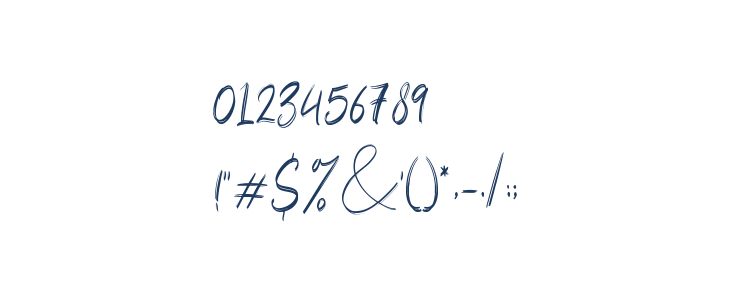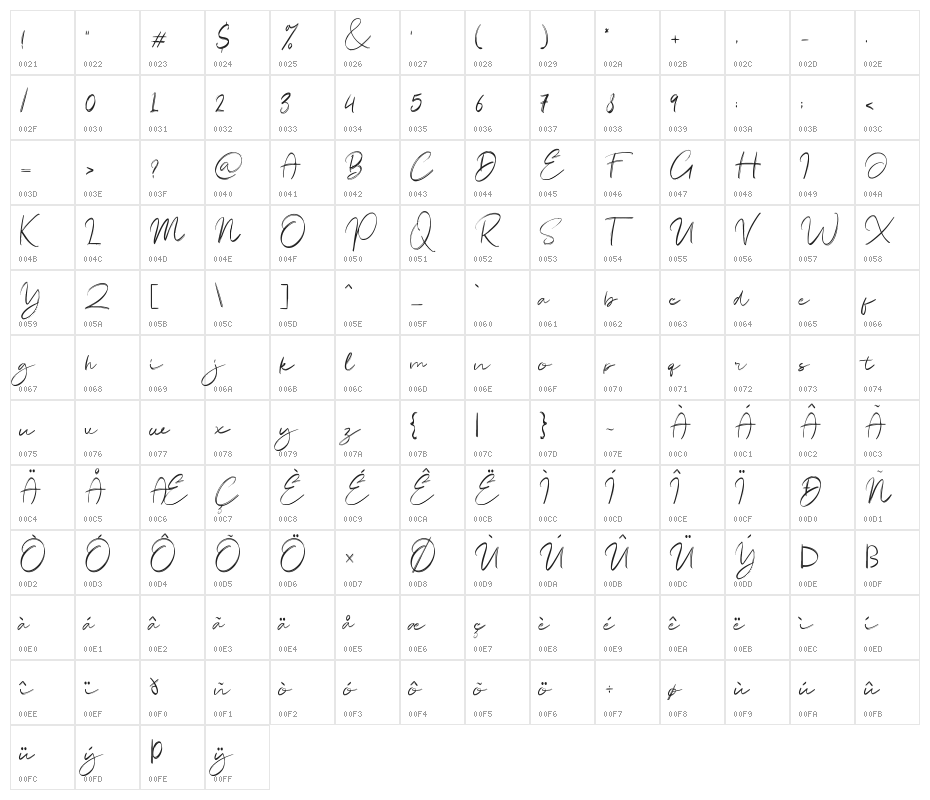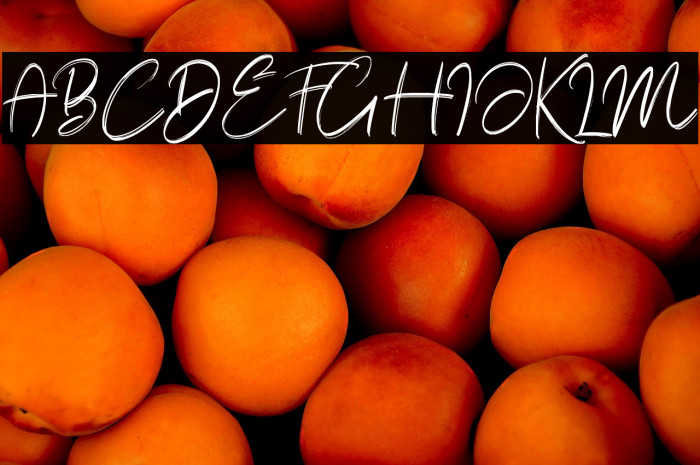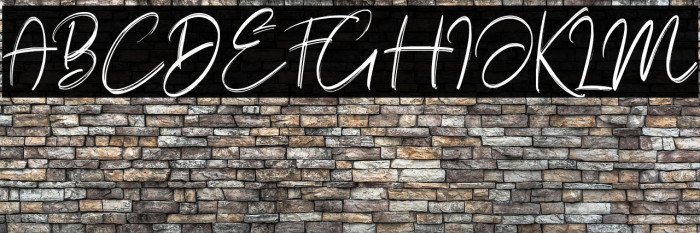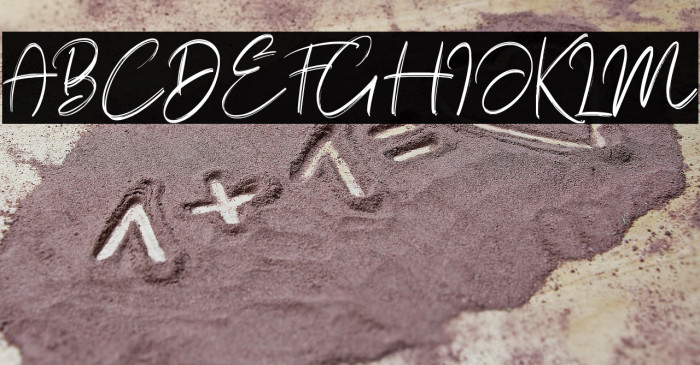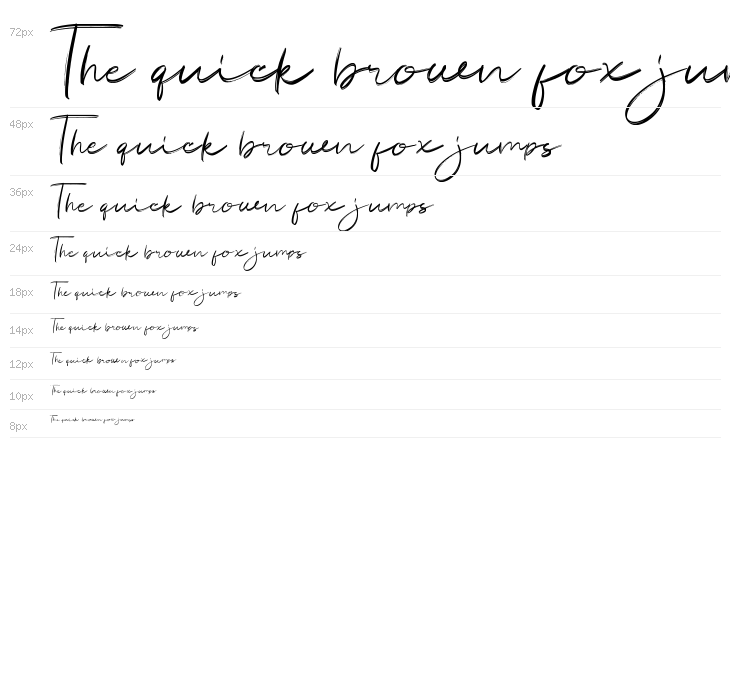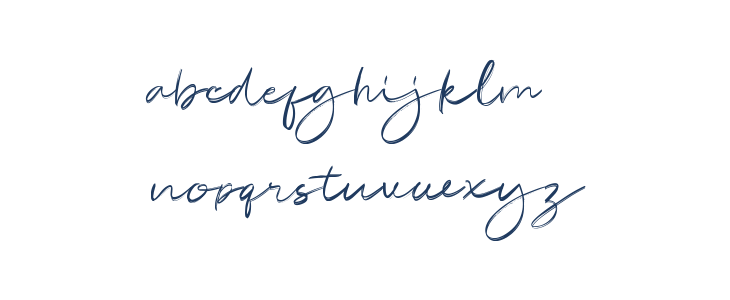
Rodetta Font
| Stile generale | Elegant, Artistic |
| Caso d'uso | Logos, Invitations, Artistic projects |
| Progetti proposti | Ideal for wedding invitations, greeting cards, personal branding, and artistic projects requiring a touch of elegance. |